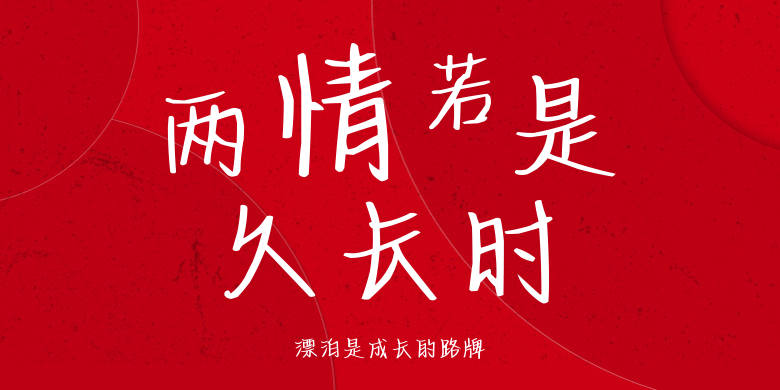
漂泊是成长的路牌
漂泊是成长的路牌,这款字体结构工整、笔画清晰,兼顾美观与易读性,适用于标题、正文、海报、包装、LOGO 等多种场景。字形优雅稳定,风格百搭耐看,适配日常排版与创意设计,让文字呈现更舒适、更具质感。漂泊是成长的路牌一笔一画,皆是细节,以均衡的比例、流畅的线条打造舒适视觉体验,字形端正大气,风格简约现代。无论是商业设计、品牌宣传还是日常排版,都能轻松驾驭,让文字更有格调与力量。漂泊是成长的路牌字体下载。